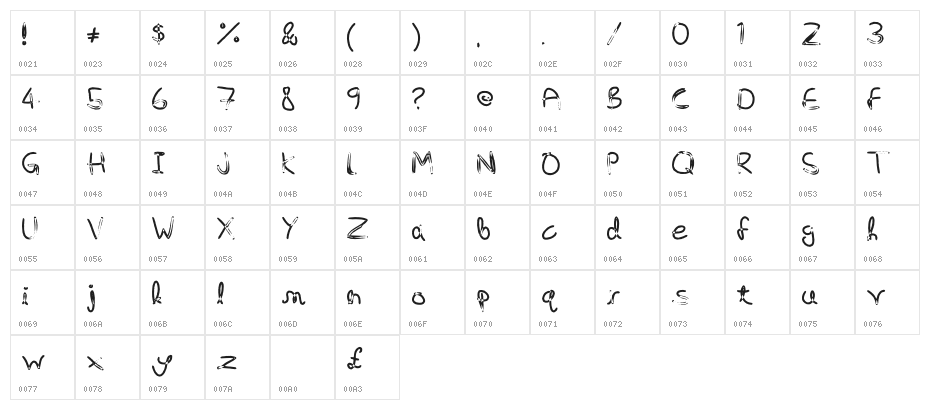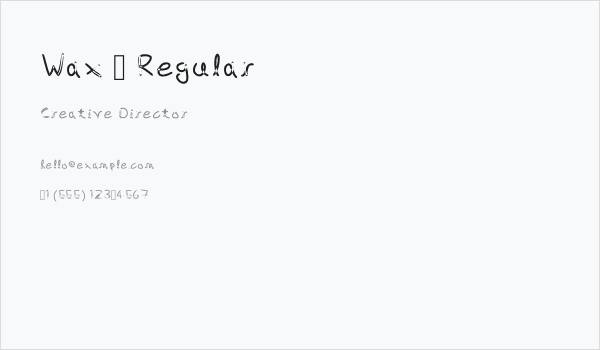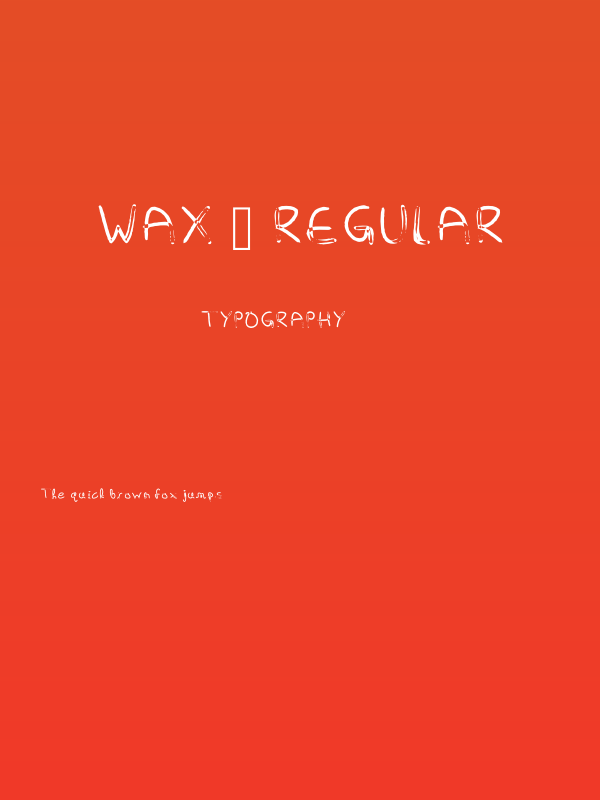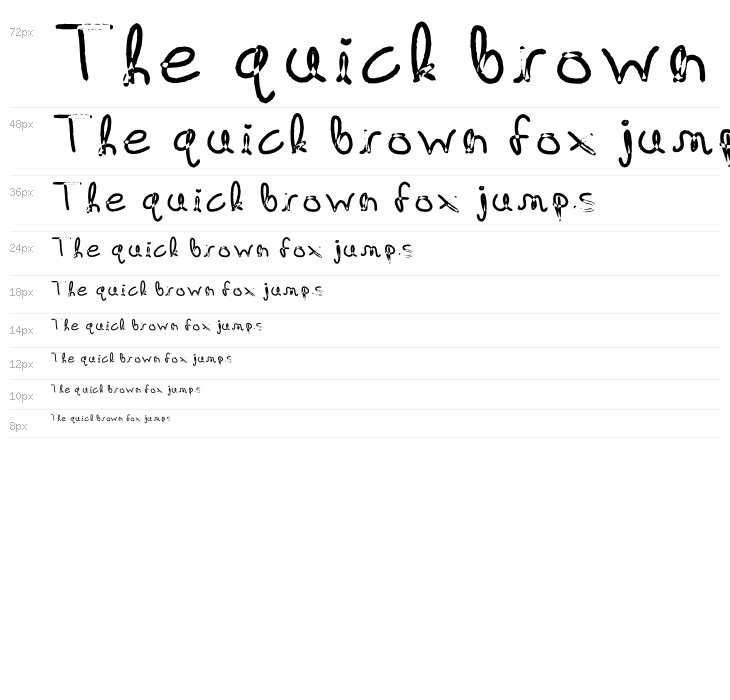
Wax - Regular Font
| Stile generale | Artistic, Expressive |
| Caso d'uso | Headlines, Posters, Branding |
| Progetti proposti | Ideal for artistic projects, posters, album covers, and branding that require a bold, expressive style. |